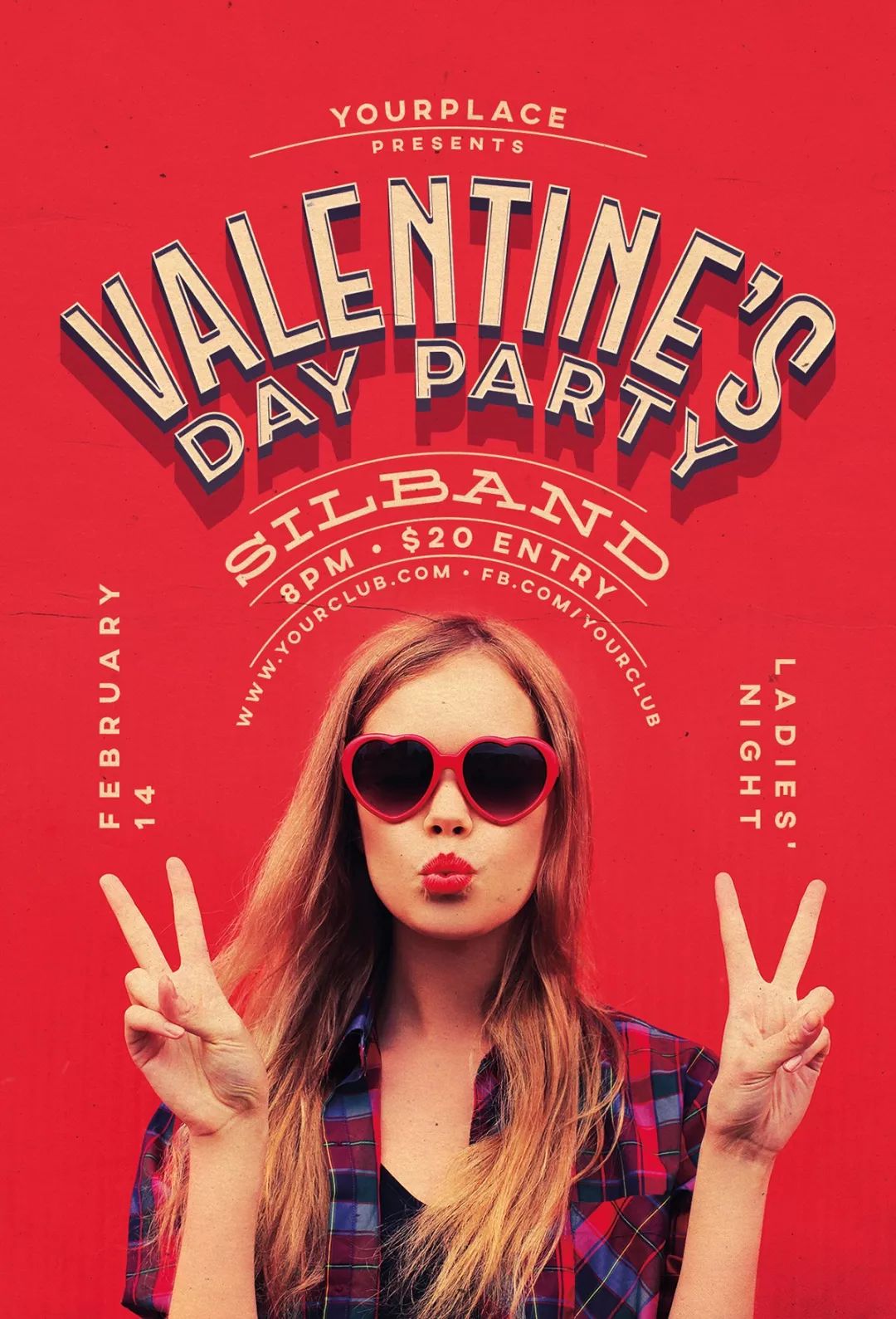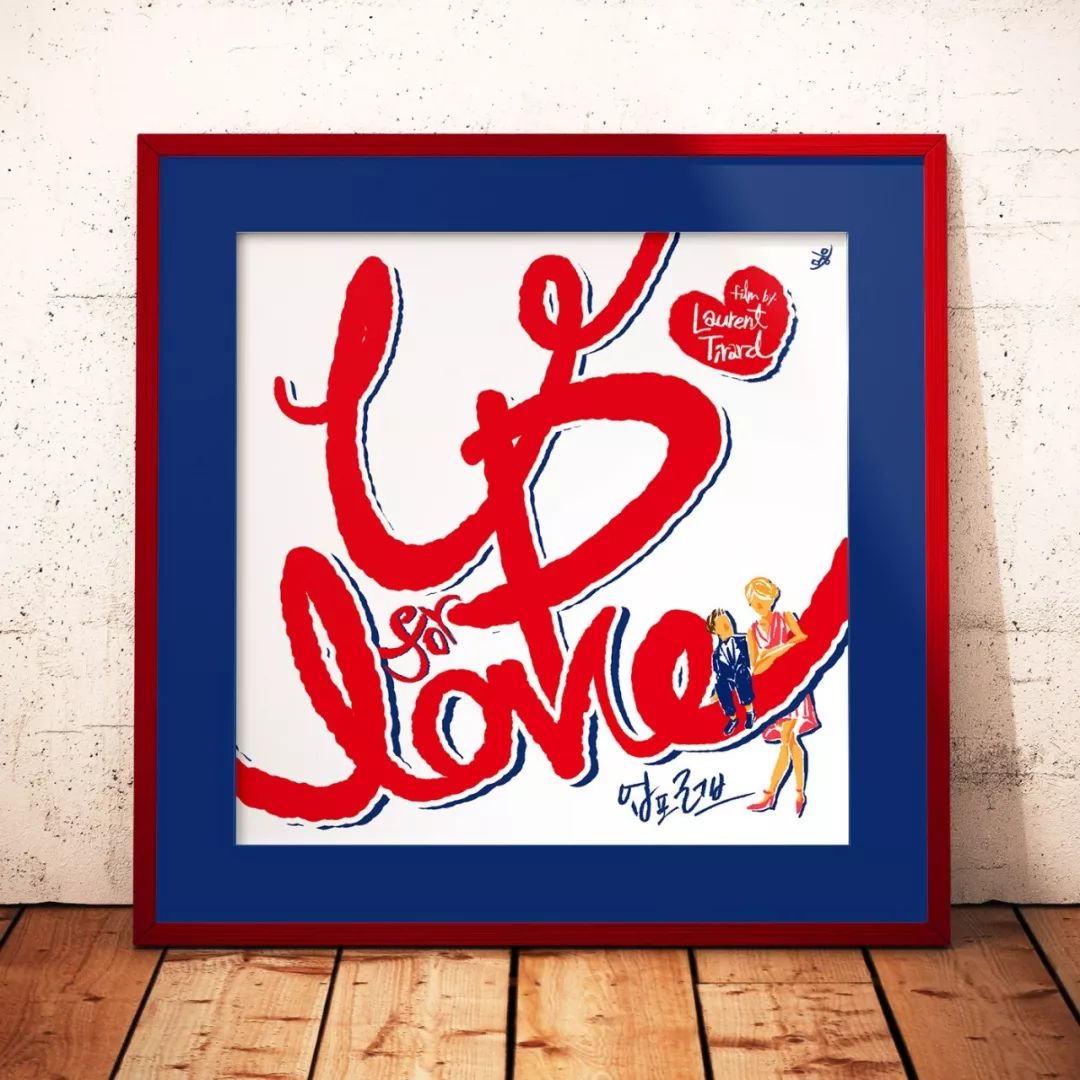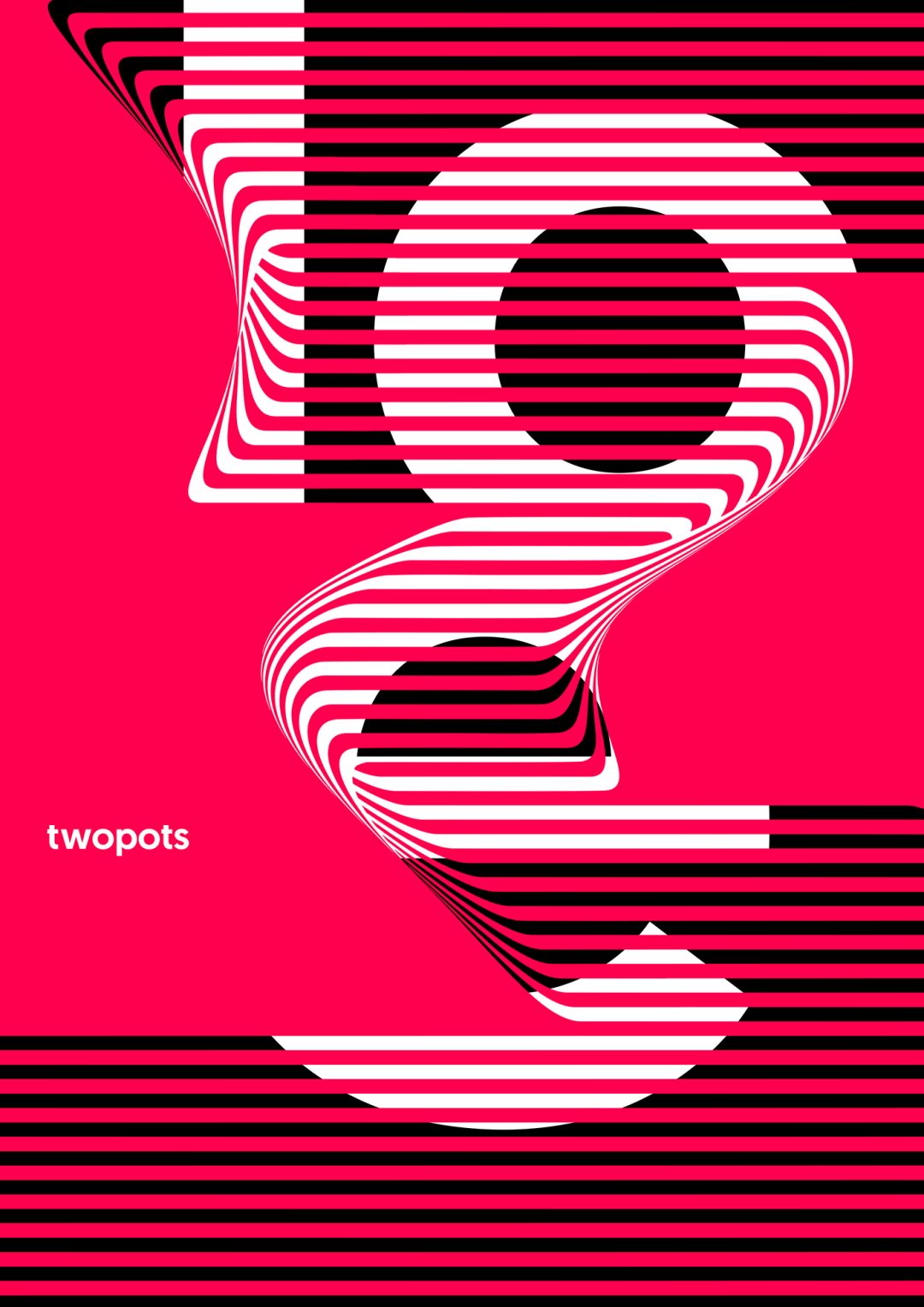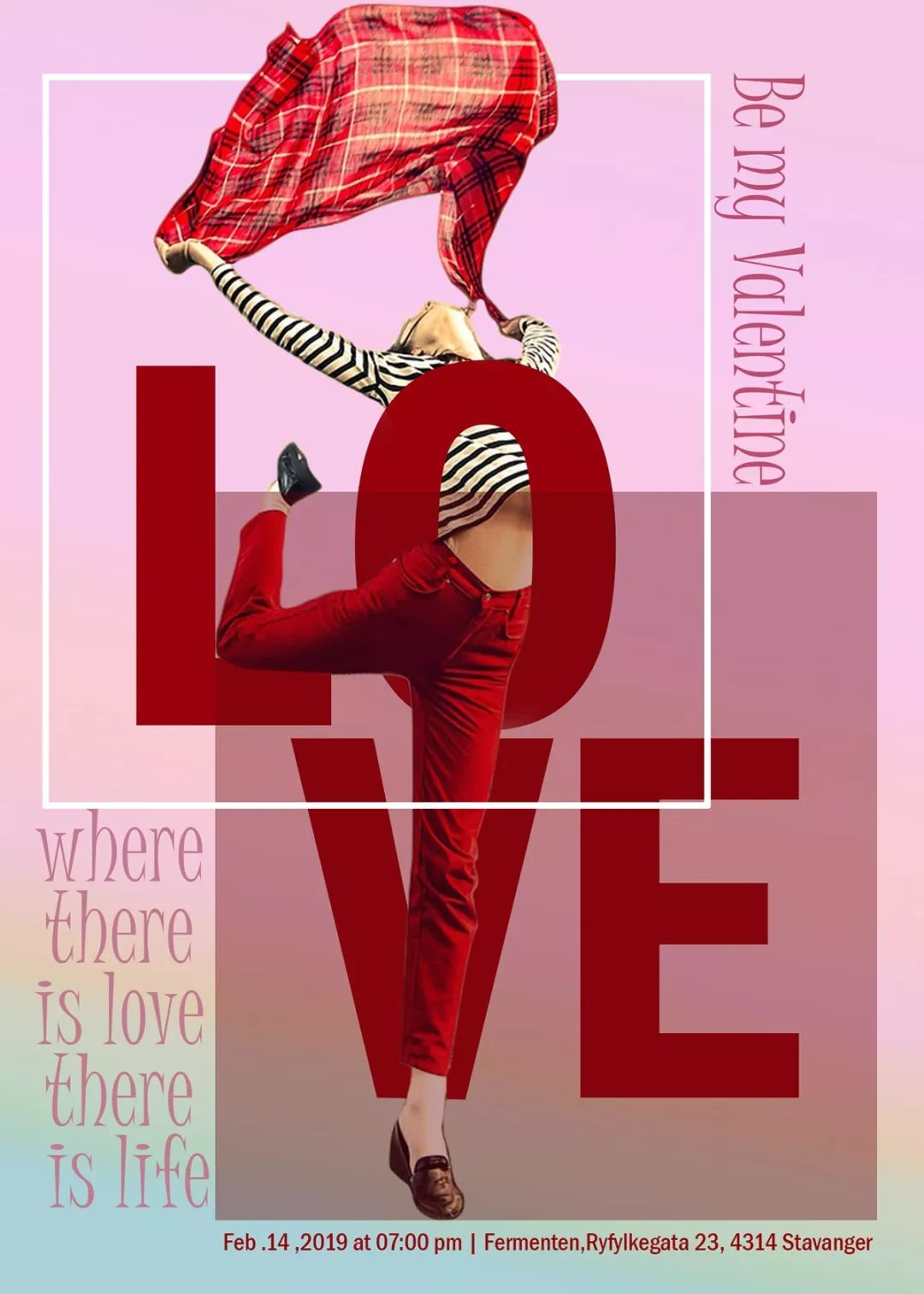
昨天柚子已经帮你们跟甲方爸爸告白了~
想要原汁原味的valentine,也可以在字由搜Radam~
杜蕾斯
老司机杜蕾斯是熄灯一小时。
不过感觉没那张流浪地球惊艳呢?
昨天还发了虐狗图,
用的是字由上的汉仪晨妹子,
被我一眼看穿。
杰士邦
好基友杰士邦还是玫瑰花、巧克力的套路。
冈本
冈本就有点看不懂了,
不会仅仅是“安排”这么简单吧?
爱慕
爱不释手这个,有点让人浮想联翩……
恰恰
如果你想更接地气,
可以一边回忆往事,
一边就把节给过了。
喜茶Heytea
排大队的喜茶,
做得像杂志封面一样,
果然是圈里的常客。
长安福特
很喜欢这个,
没有一点粉色,
却满屏幕都是么么哒~
OPPO
也有“只动手不动口”的,
敞开心扉,给你看!
联想
但是情话说得好,
也是一种能力,
我希望你有。
国外版
可能是过腻了这个节,西方在海报设计上,更多的是字体、版式的变化,就像是去掉了多余的两点,直爱~
字由版
大家都这么热闹,我们当然也要来借势,由Adobe与Fontself合作推出的情人节字体,风格独特、自带效果,最重要的是免费商用,目前字由上已有3款,赶快用起来~